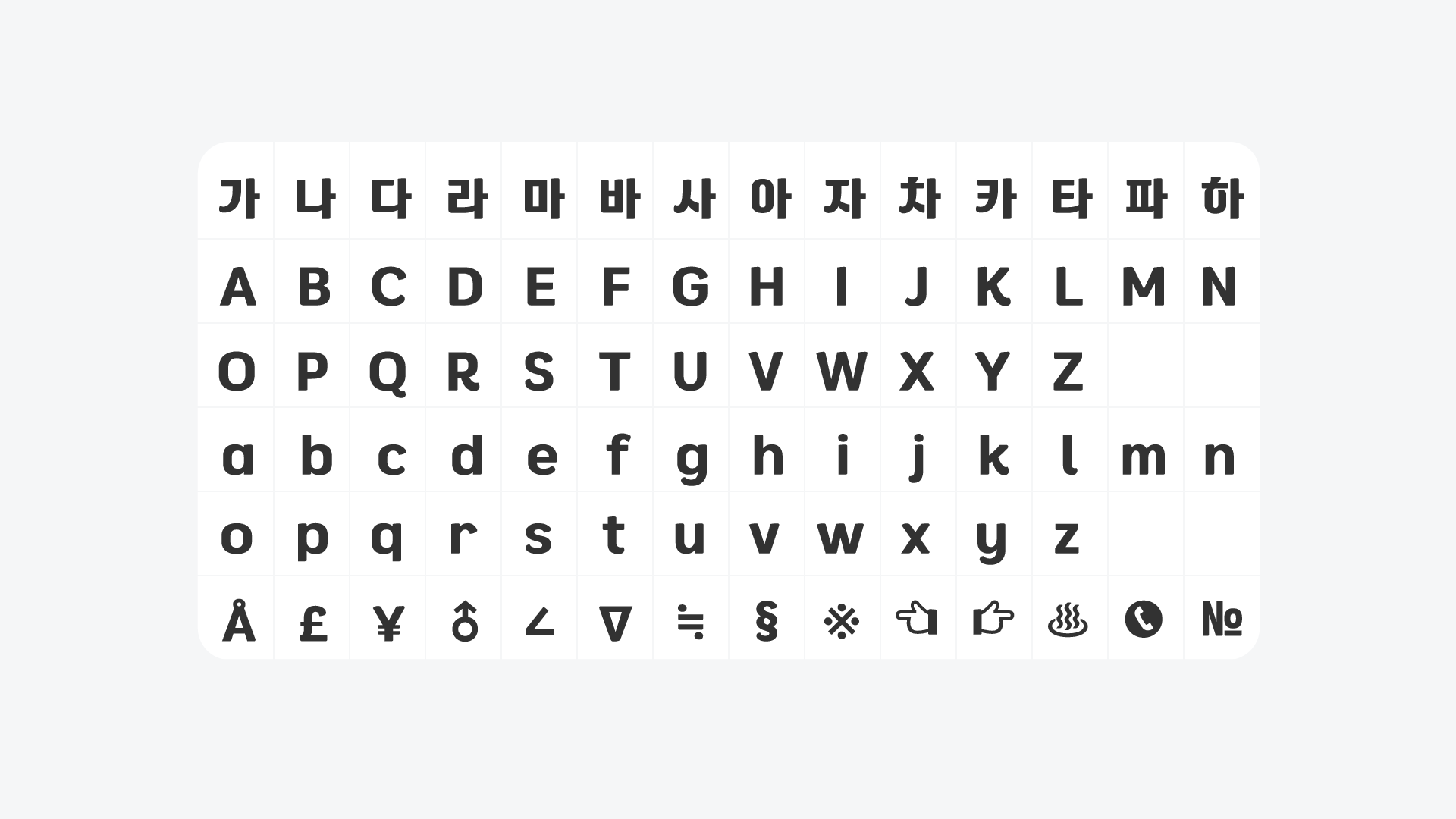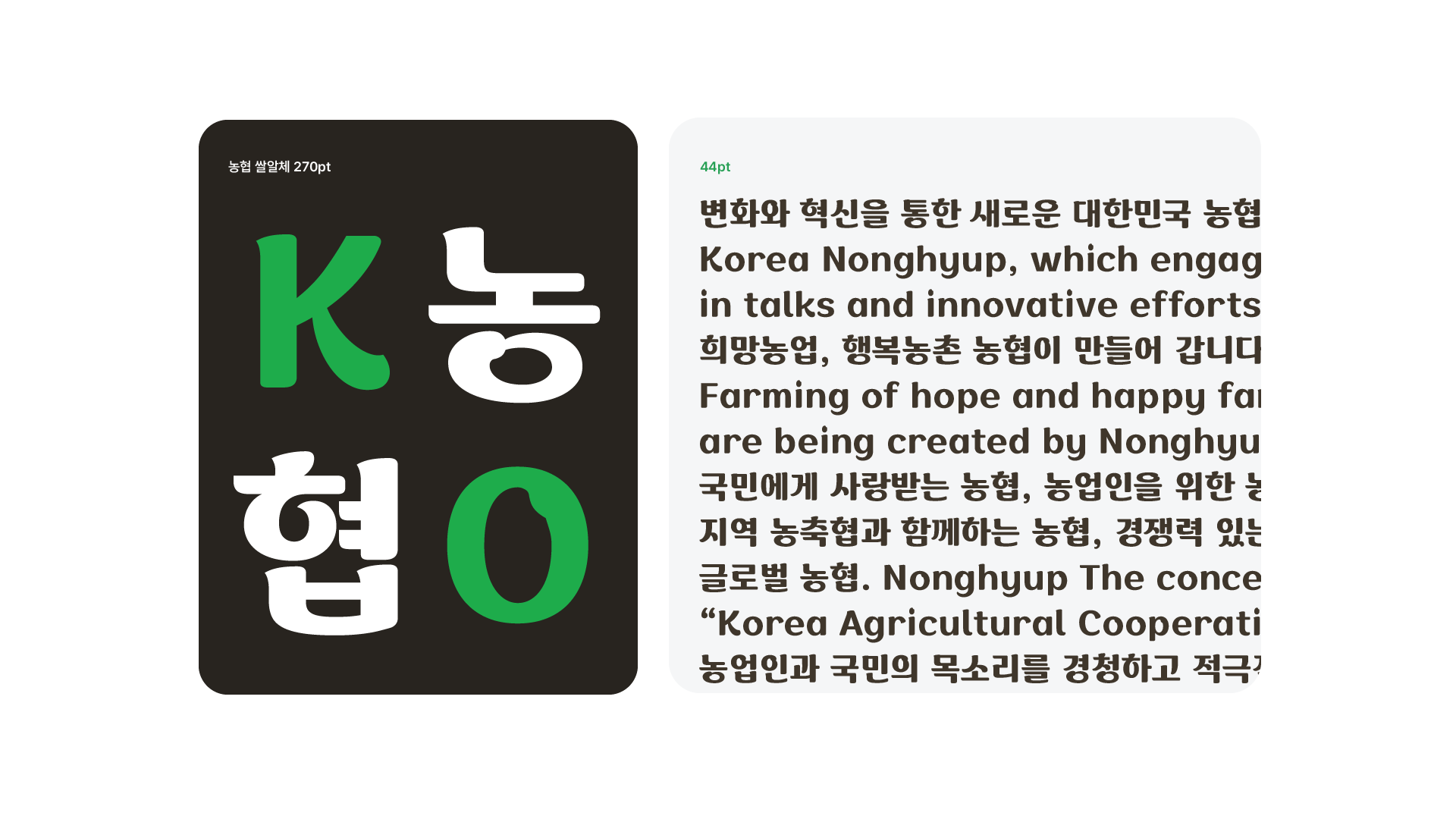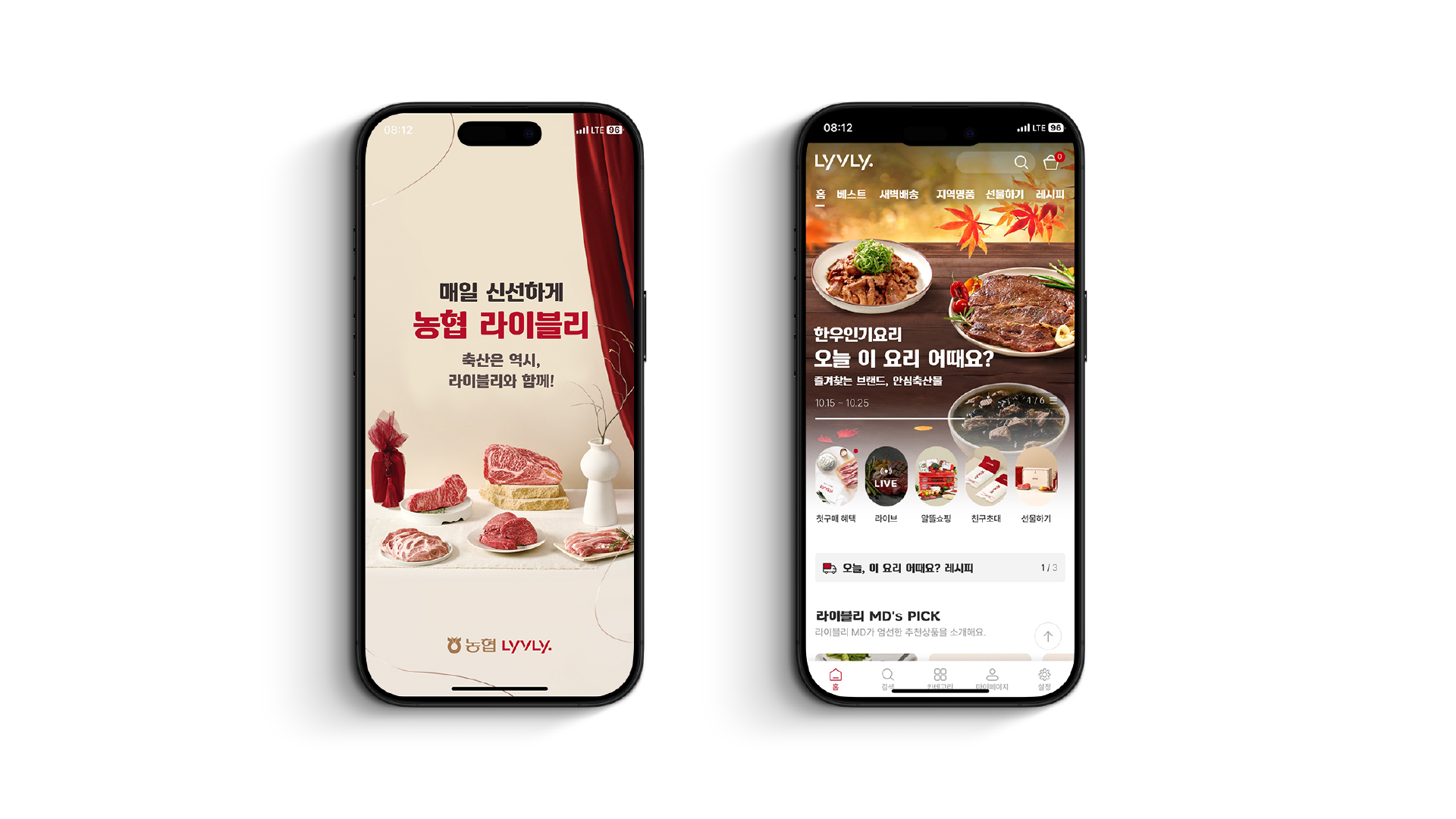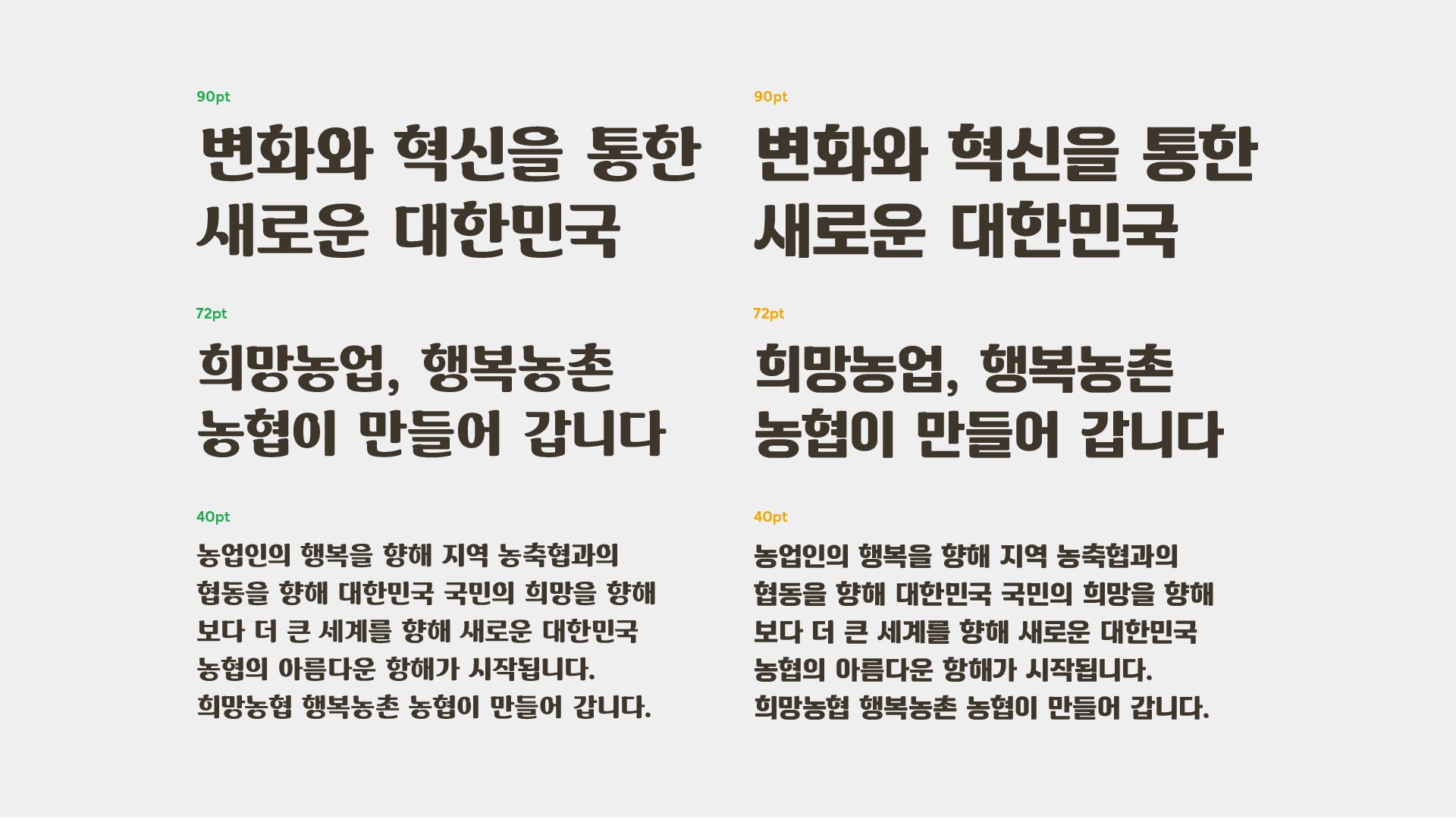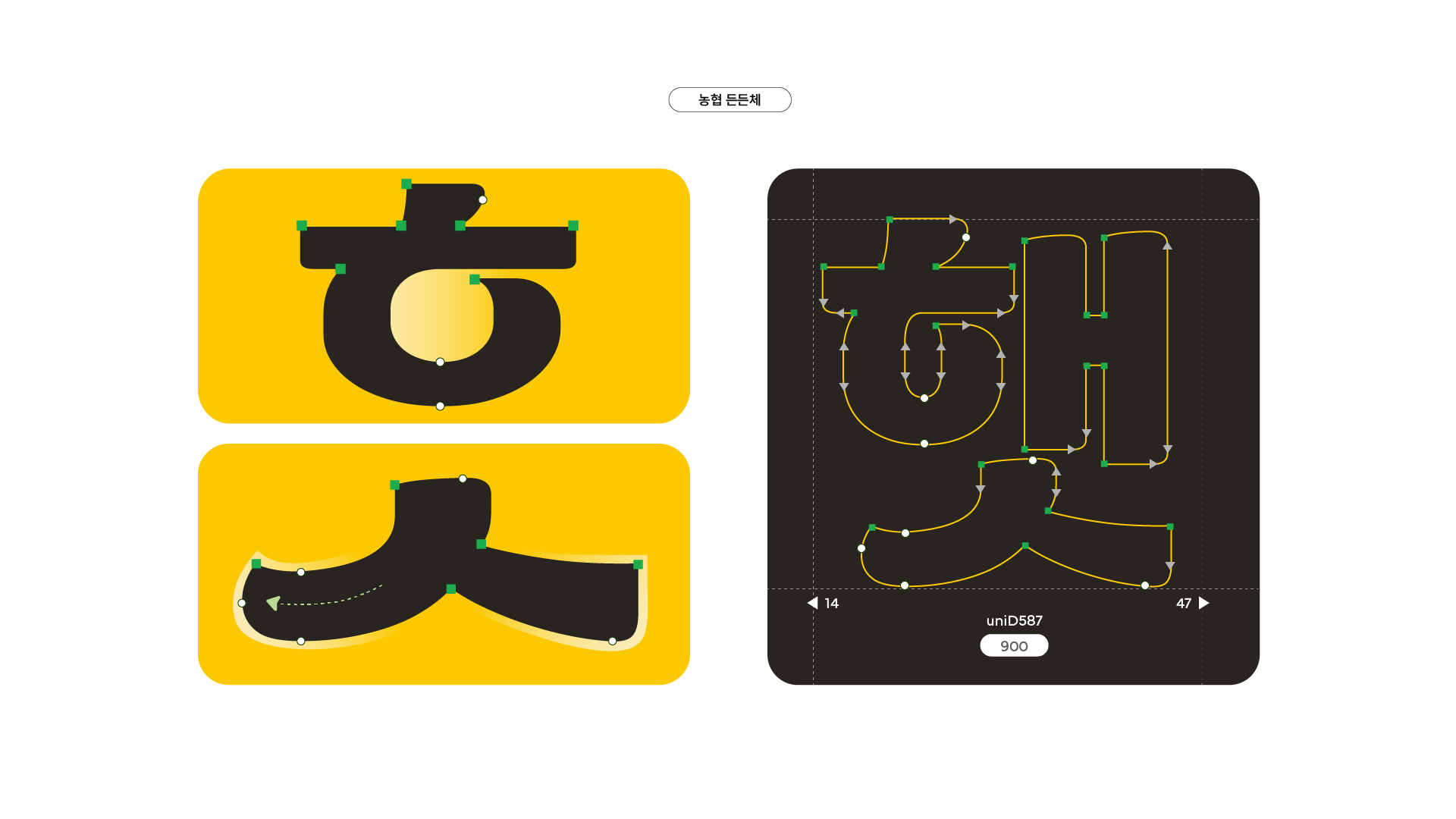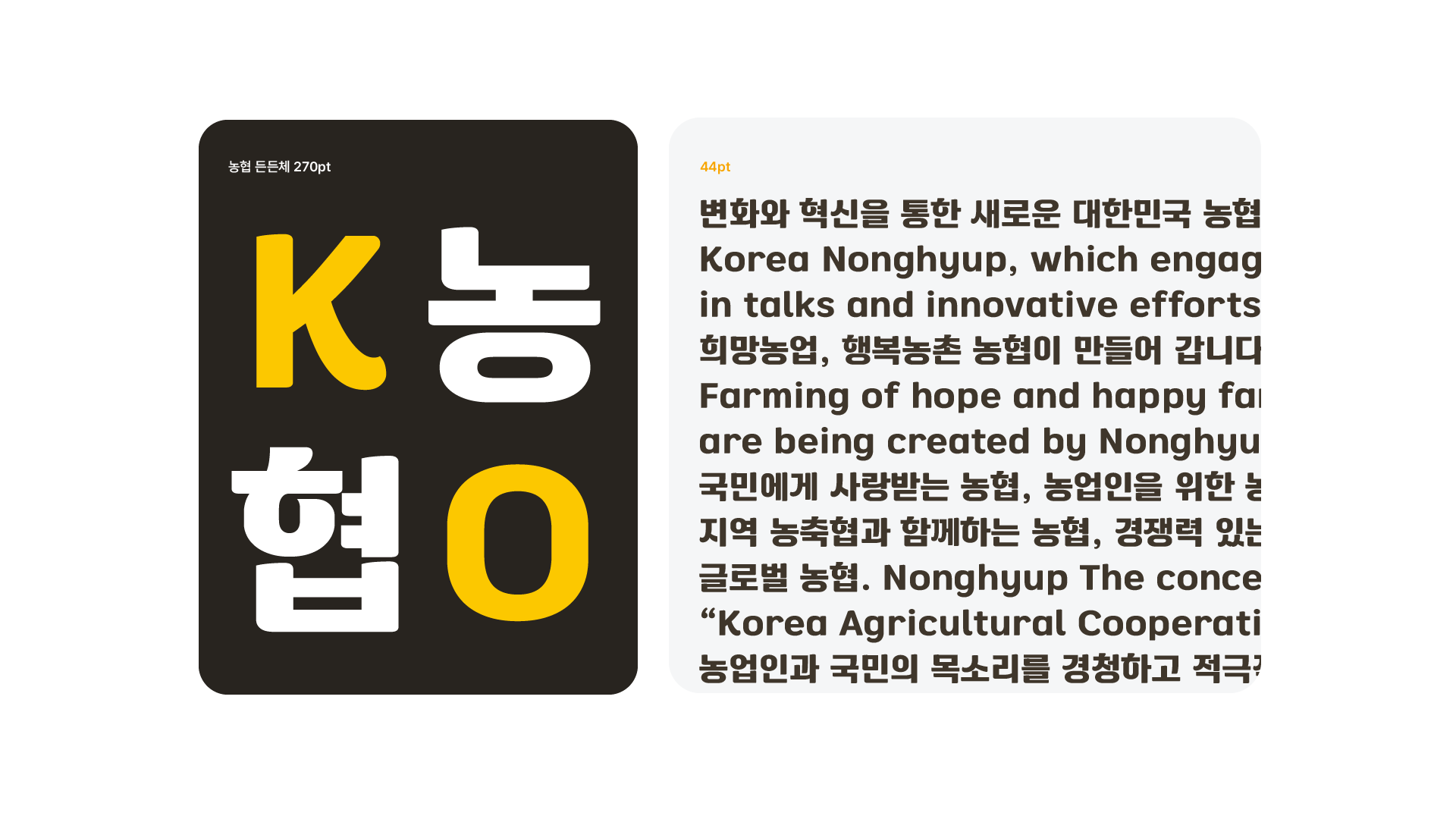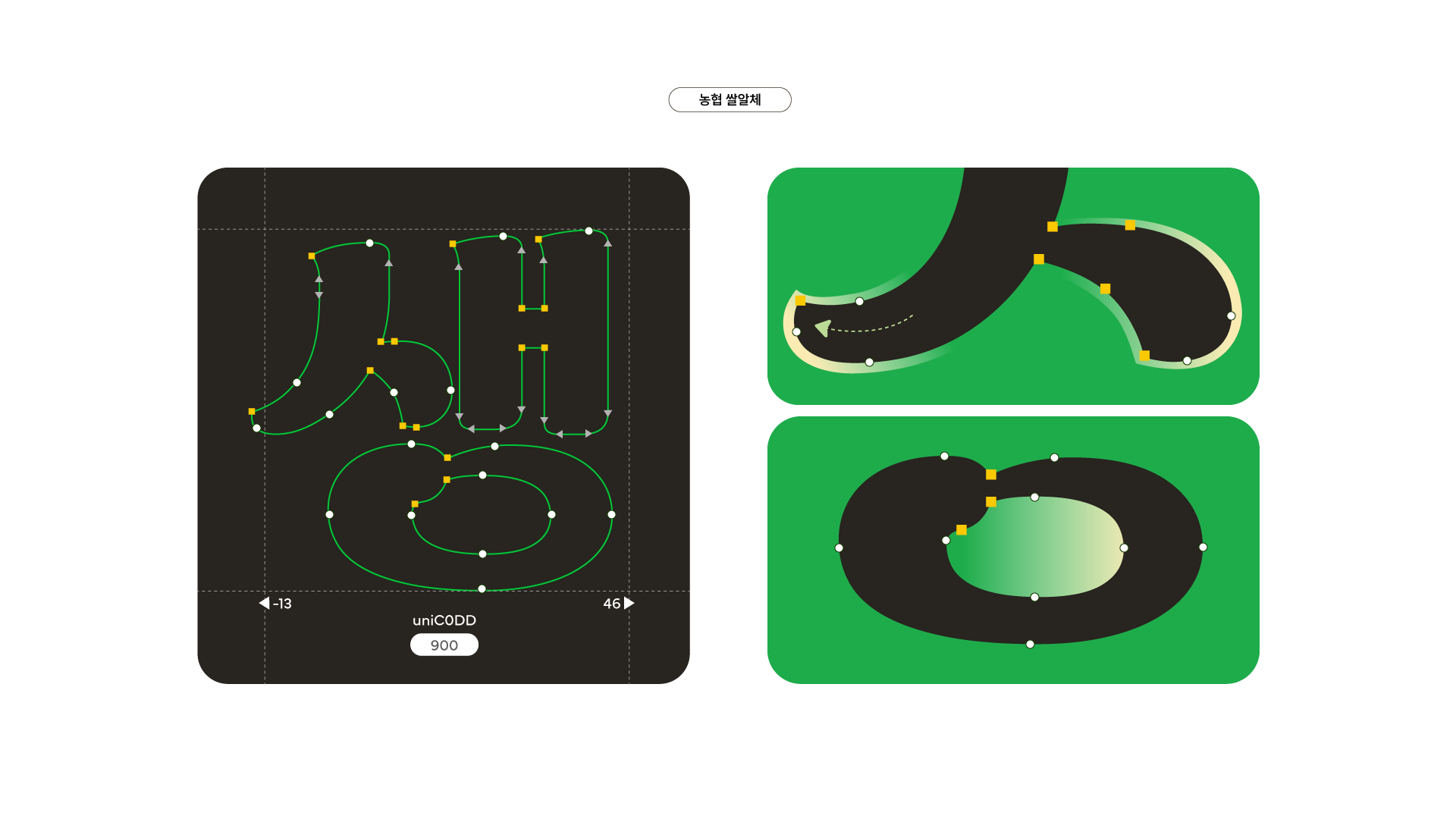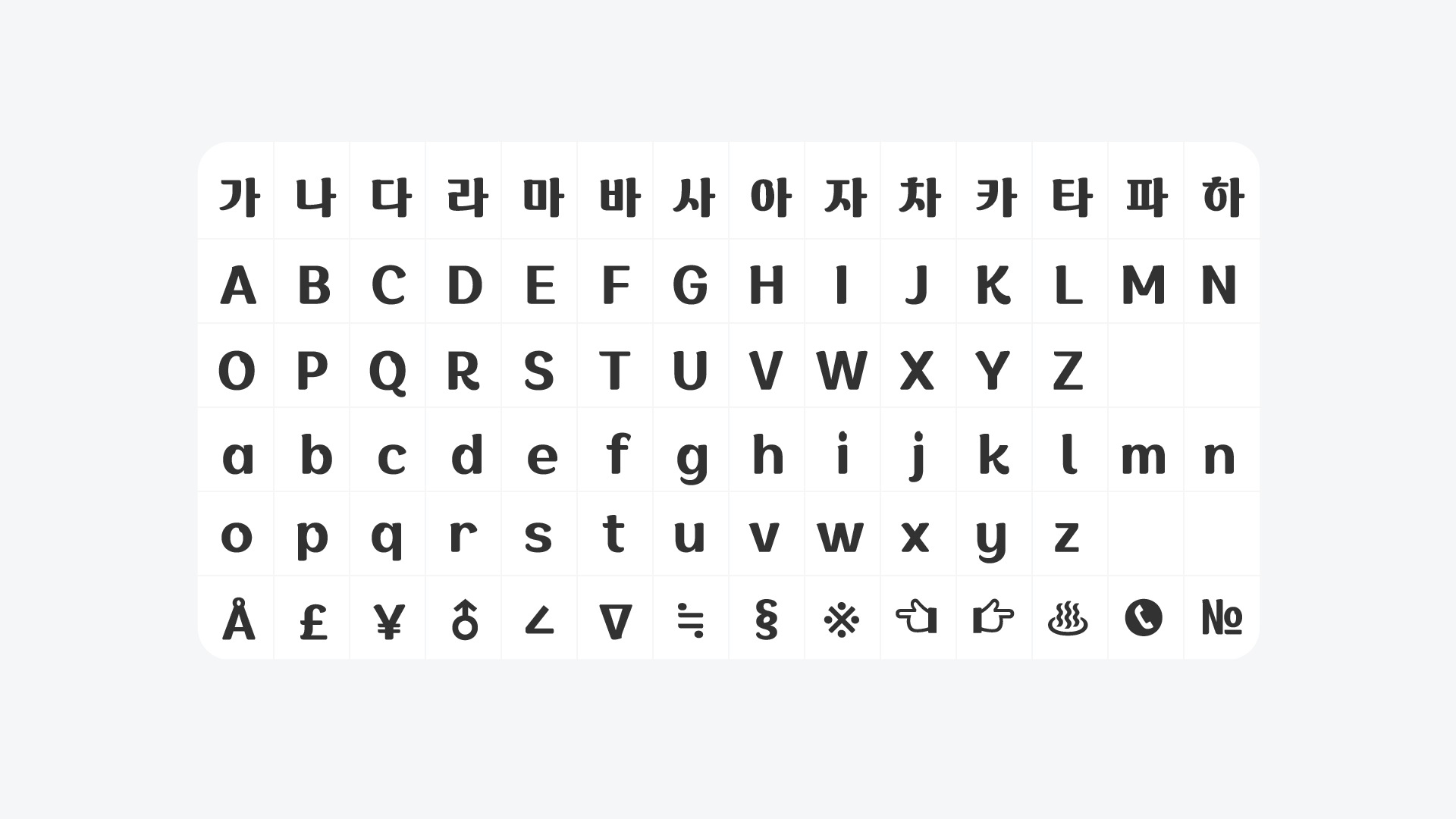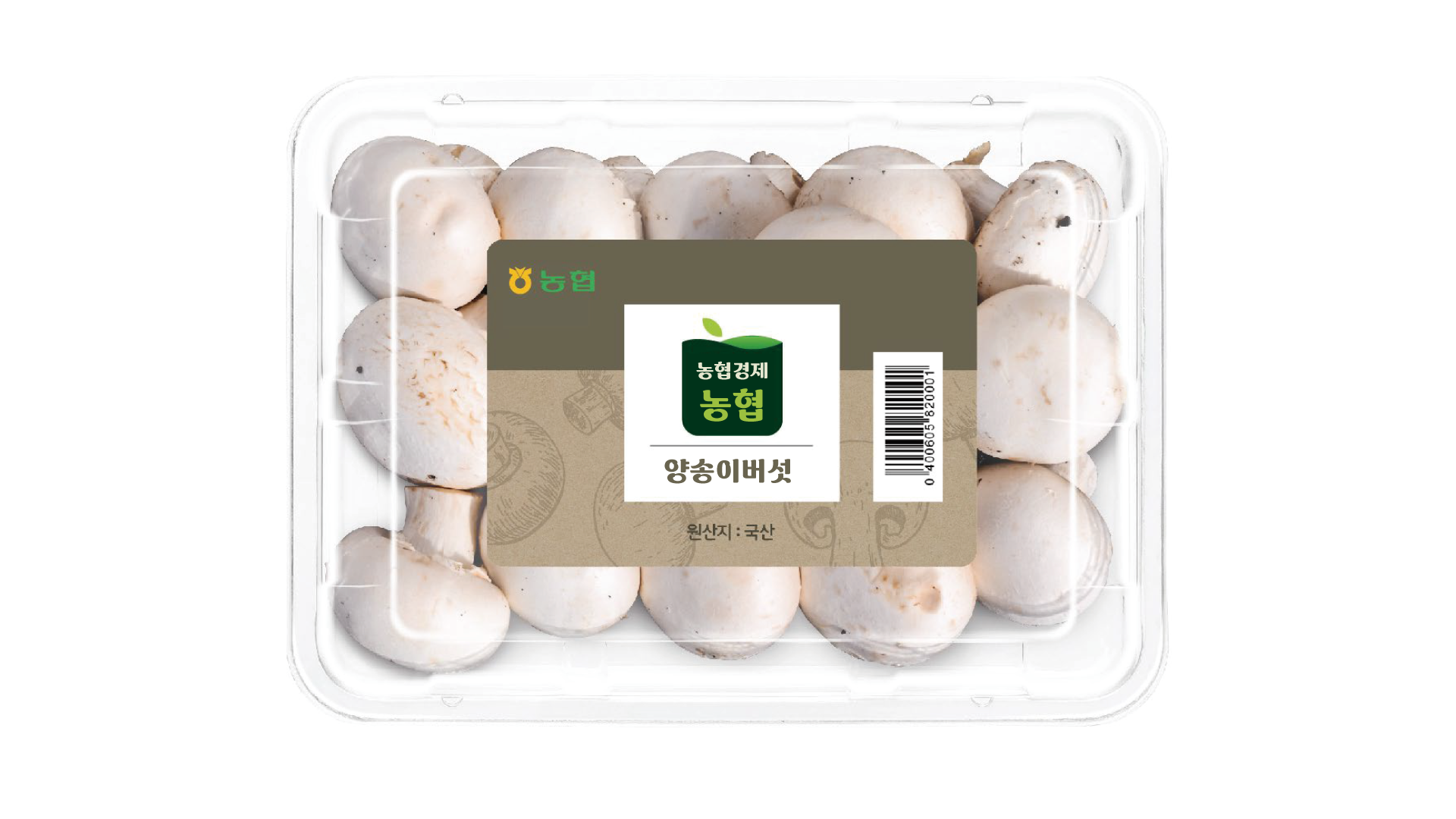
농협 쌀알체
손으로 쓴 듯한 곡선의 획을 사용하여 농협의 친근함과 편안한 이미지를 담았습니다. 자소 ‘ㅇ’에 쌀알의 형태를 담은 것이 큰 특징으로, 농가 경제와 국민의 삶에 기본이 되는 농협의 발전을 상징합니다. 획 대비가 있는 굵기 표현으로 제목용으로서의 개성이 극대화됩니다.
농협 든든체
곡선과 직선을 함께 사용하여, 농협의 친근함에 더하여 든든하고 신뢰감있는 이미지를 담았습니다. 획 대비가 없는 굵기 표현으로 힘 있는 이미지를 극대화하여, 농협의 전문성과 스마트함을 전달합니다.
서체 이름
서체 종수
글자수
출시년도
농협 쌀알체, 농협 든든체
각 1종
한글 2,350자, 영문 Basic Latin 95자, KS심볼 986자
2024